宋体,黑体,楷体,仿宋……这些熟悉的汉字字体,早就悄无声息地渗入了我们的日常生活中。然而,当你翻开书本阅读,或是在电脑键盘上敲下一个个汉字时,可曾想过,这些汉字字体从何而来?是由什么人设计的?
10月14日,在上海市新闸路1209弄60号的印研工坊,上海印刷集团和上海印刷技术研究所举办了揭牌仪式,在仪式上揭开两块牌子,分别是“现代汉字印刷字体发源地”和“上海印刷字体展示馆”。人们最常使用的宋、黑、楷、仿四种字体,正是诞生于此。
揭幕仪式。 上海印刷技术研究所供图这里是现代汉字印刷字体的发源地作为“现代汉字印刷字体发源地”的上海印刷技术研究所成立于1956年,原址正是在新闸路1209弄60号。2019年上海印刷集团和上海印刷技术研究所在“印研工坊”园区改建结束后,搬回上海市新闸路1209弄60号,在新改建后的“印研工坊”园区里处处可见对印刷文化、字体文化的展示。
在印研主楼的一至二楼,专门留出了近一百平方作为“上海印刷字体展示馆”,其中从前言开始到正式走入“字体馆”前,用非遗传人墙的方式,介绍上海印刷技术研究所乃至中国字体界都有着举足轻重地位的一代、二代、三代23位非遗传承人及他们的主要贡献,是这23位传人带领着上海印刷技术研究所字体室从无到有、辛苦创业;在一楼半的“字体馆”分为“源远流长、繁花硕果、继往开来、经典传承、创新发展”五个部分,让不熟知印刷字体的参观者对印刷字体的发展和书写技艺的传承在参观、互动的同时有所了解;二楼的“非遗馆”更为全面的介绍了上海印刷技术研究所“宋、黑、仿、楷”四大印刷字体的创写背景和应用、源于实践、指导实践的书写技艺标准——《汉字印刷字体设计规范》等珍贵文献、上海印刷技术研究所在字体创写方面取得的荣誉奖项。而为了让更多人了解现代汉字印刷字体的起源和发展,了解汉字印刷字体的设计规范和创写工艺,更好地宣扬与传承汉字文化、字体文化、非遗文化,这一座“上海印刷字体展示馆”,也即将对公众开放。
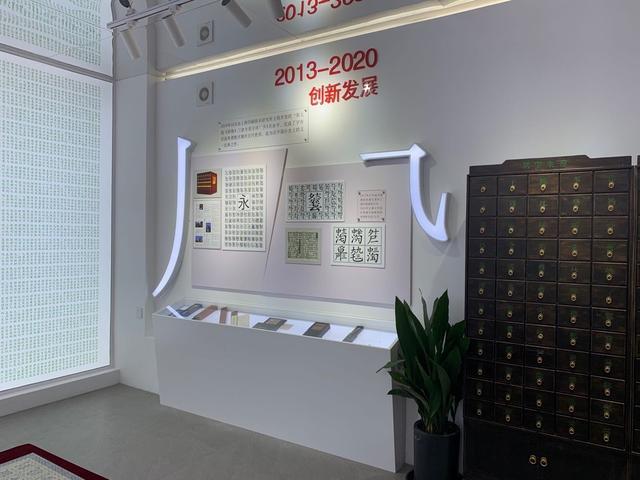
“上海印刷字体展示馆”的一角。 澎湃新闻记者 程千千 图上海印刷技术研究所之所以可以成为“现代汉字印刷字体发源地”是因为两个“源头”。一是新中国的印刷字体诞生在上海市静安区新闸路1209弄60号上海印刷技术研究所。在相当长的一段时期,我国汉字字体、字形杂乱,异体、变体混合使用,严重影响印刷质量和阅读效果,更导致我国参加国际书籍装帧博览评比无功而返。1959年,文化部召开会议指导上海率先进行“印刷字体改革”,以印研所为基地,在新闸路1209弄60号内集聚了沪上美术创意有功力、书写正楷有造诣、雕刻字模有经验的三结合人才,成立了有50多人组成的字体研究室。印研所字体研究室的设计人员耗时5年,相继完成了宋、黑、楷、仿四种常用印刷字体的创写设计,总计8万字,为新中国推广简化字和汉字使用的规范化作出了巨大的贡献。由印研所原创的宋、黑、楷、仿四种新字体,分别用于印刷新版横排本《毛泽东选集》、《辞海》、《汉语大字典》以及万千种政、经、科、教图书,期刊杂志,幼少课本,使我国出版物和印刷品面貌焕然一新,使各年龄层次的读者视觉舒适、赏心悦目,取得了良好的社会与经济效果,多次获文化部、新闻出版署和上海市重大奖项。经历近半个世纪的时间考验和实践证明,这几种字体被业界视为字体中的经典。二是汉字印刷字体的数字化发展也始于上海印刷技术研究所。20世纪80年代,上海印刷技术研究所将宋、黑、楷、仿四大品种的专用字稿作为同英国蒙诺公司合资的投资,首次购进国际先进的激光照排设备。后又将这四种字体的原始字稿,全部复印无偿提供国家“748”工程、“汉字信息处理”重大项目,为我国印刷业实现告别“铅与火”的技术革命做出了贡献。北大方正的王选教授将这些字体与现代数字信息技术相结合,成为发明“汉字信息处理激光照相排字技术”的原创母体,之后普遍进入海内外汉字字库,派生再造出千姿百态、各有特点的后代字体。目前国内普遍应用在计算机系统字库里的宋、黑、楷、仿四副常用字体品种,无论是国标字数的增加还是品种的扩展,它们的笔形、结构、重心、粗细等内外形基本框架及其神韵,都源于上世纪上海印刷技术研究所创写的印刷字体。
“宋黑仿楷”四大字体是怎样创写的
1959年,我国参加莱比锡国际书籍装帧博览会评比无功而返,严重影响图书质量的印刷字体,引起业界的高度关注。当时的文化部出版局总署长胡俞之在护照及印刷字体改革座谈会明确提出要提高图书报刊的印刷质量,首先要改革印刷字体,1961年上海印刷技术研究所借助上海丰富的出版印刷资源,依靠上海书法美术科技人才集中的优势,率先开启了汉字印刷字体传承书写工作。
1962年,宋体二号和黑体二号被列入1963年至1972年国家科学技术发展规划,命名为创新汉文印刷字体中心课题。上海印刷技术研究所以常用的主流字体宋体字为重点,对宋、黑、楷仿4种正文常用字体全面整旧创新。为了书写宋、黑、楷、仿四种新字体,课题组成员广泛查阅了宋元明清各代数百种善本字体,参照了当时常用的铅印字体样本,结合汉字繁简对照表和印刷通用汉字字形表的要求,经过反复的实践探索,制定了汉字印刷字体设计规范,作为评判字体质量的标准,有效地指导了字体设计工作。
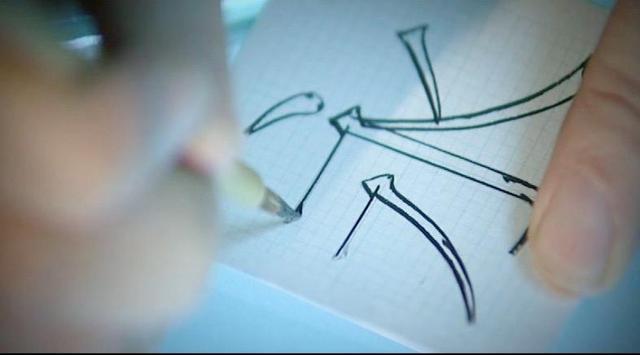
字体设计过程。上海印刷技术研究所供图印刷字体的创新有5道工艺程序。第一步是写铅笔稿,作为字体创新的关键环节,这一步骤要求设计师必须有书法和美术的功底,按照印刷通用汉字字形表和汉字印刷字体设计规范的要求,融入艺术创意,在专用稿纸上精心勾勒出字体轮廓,要求线条清晰,笔画粗细分段合理,形态准确,结构协调,重心平稳,为每个字的质量和整幅字的风格奠定基础;第二步是划线,操作者必须熟悉笔画粗细规范,用直线笔沿铅笔稿上的直线画出光洁一致的黑色线条;第三步是勾线,操作者必须熟悉笔行规范,将铅笔稿中的点、撇、捺、钩调等曲线形笔画勾出清晰轮廓,同时描好横竖笔画的起笔、收笔的笔形装饰;第四步是填墨,在勾画好直线曲线的墨稿上,擦出遗留的铅笔线条,然后填满黑色,要求浓淡均匀前后一致,不出线外;最后一步是描白,用白色国画颜料兑字稿进行精细调整,去除毛刺,圆润笔画,达到边界清晰,光洁挺拔,姿态优美。在即将开放的“上海印刷字体展示馆”内,陈列了大量的字体设计的原稿,很多纸张都已发黄,但观者依然可以透过漫长的岁月,感受到设计师和操作者的精湛技艺与用心。
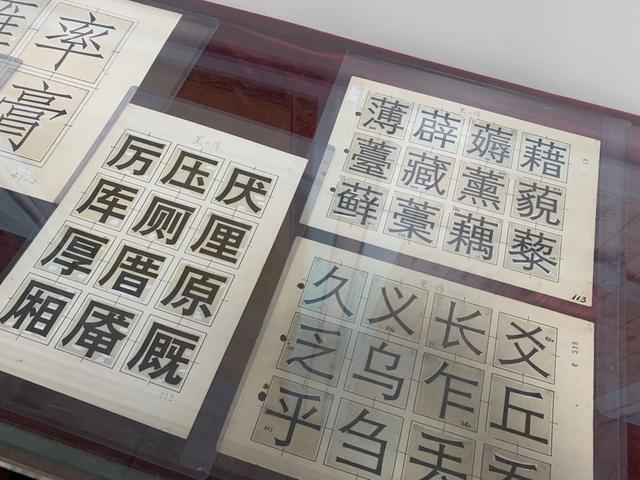
展出的字体设计原稿。上海印刷技术研究所相继创写出宋体一二号、黑体一二号、楷体、仿宋体4种6副新字体,这是传统书法艺术、工艺美术和刻字技术综合再造的成果,有鲜明的时代特征。为适应社会需求,4种字体的数量不断扩充,尤其是宋体已达到7万多字,不仅是现行多种宋体字库的母体,更是具有历史价值、记忆价值和社会价值的文化珍宝。在创写字体的同时,上海印刷技术研究所还根据标准化、规范化的笔形、字形编制出一份《印刷通用汉字字形表》,报经国家文字改革委员会审核通过,作为文改委颁发的我国印刷汉字模板,供出版各种辞书、百科全书等工具书,政治、科技、文艺书、教科书,以及报纸、期刊的标准印刷汉字字形的依据。印研所字体室是最早的把手写体与印刷体统一,独创出新的笔形舍弃老的繁重笔形,如今各大报刊书籍简化字体沿用至今。